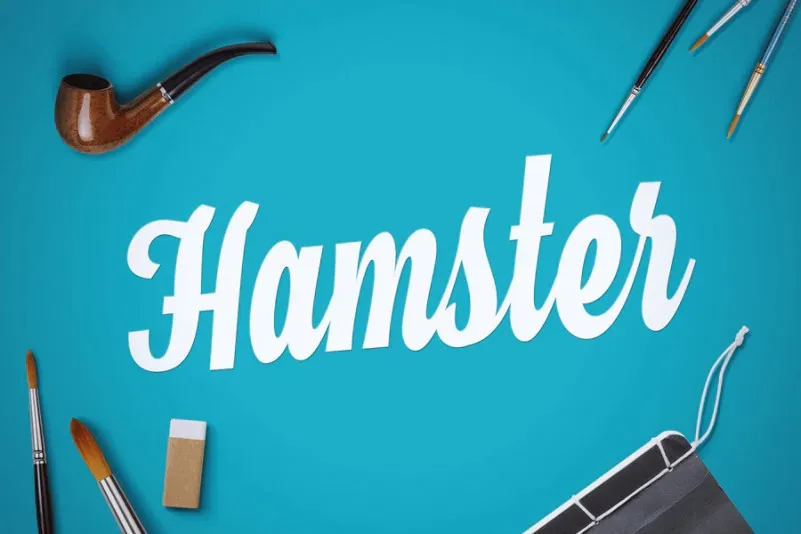
Hamster Script Font – Download Grátis
A Hamster Script Font é uma elegante escolha para quem busca um estilo sofisticado e moderno no seu trabalho de design. Com suas linhas fluidas e elegantes, ela se encaixa perfeitamente em qualquer projeto que você estiver criando. Essa fonte foi especialmente concebida para aplicação em logos e outros formatos formais, como convites, rótulos, logotipos, revistas, livros de leitura, cartões de agradecimento ou anúncios de casamento, embalagens, beleza, material escolar e novelas. Com sua elegância perfeita para uma fonte moderna e chic, é um must-have para qualquer coleção de fontes modernas e sofisticadas. Seja você um designer de logotipos ou criador de revistas, essa font oferece o que há de melhor em estilo script moderno e sofisticado.